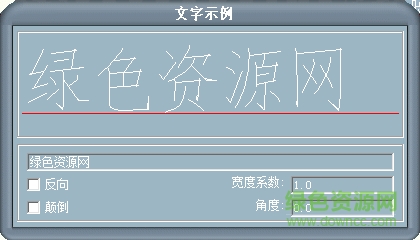
lytxt.shx字體是一款外形和宋體類似的cad字體應(yīng)用。如果用戶在查看cad圖紙時,又遇到系統(tǒng)缺少lytxt.shx的情況,也不用著急,可以在本站免費下載解決!
lytxt.shx字體是autocad軟件的大字體,在打開CAD圖紙的時候,有時會提示需要這種lytxt.shx字體的選擇,如果沒有這個lytxt.shx字體的支持,那打開的DWG圖紙里的文字就會出現(xiàn)問號。需要的用戶歡迎在綠色資源網(wǎng)下載。